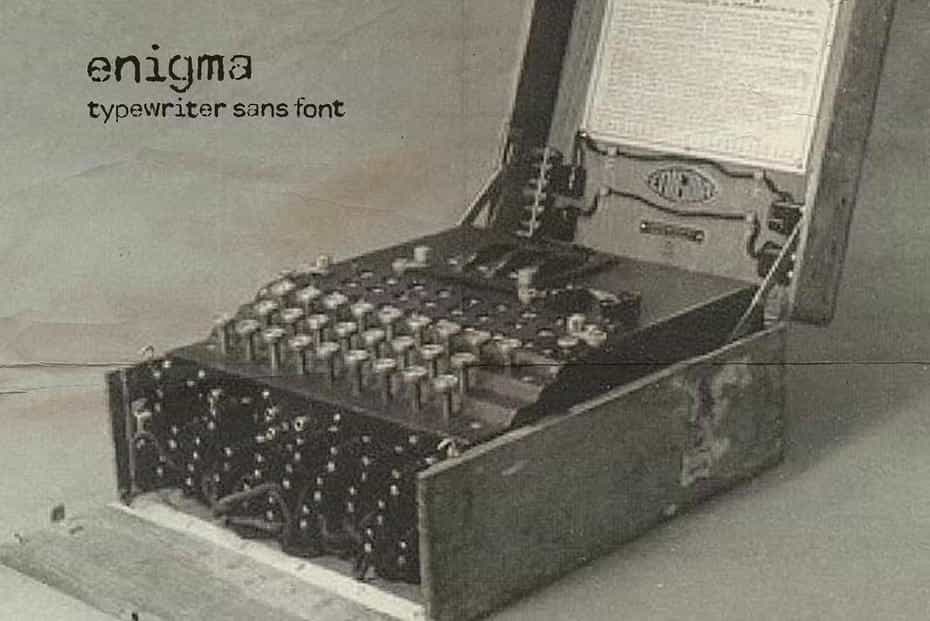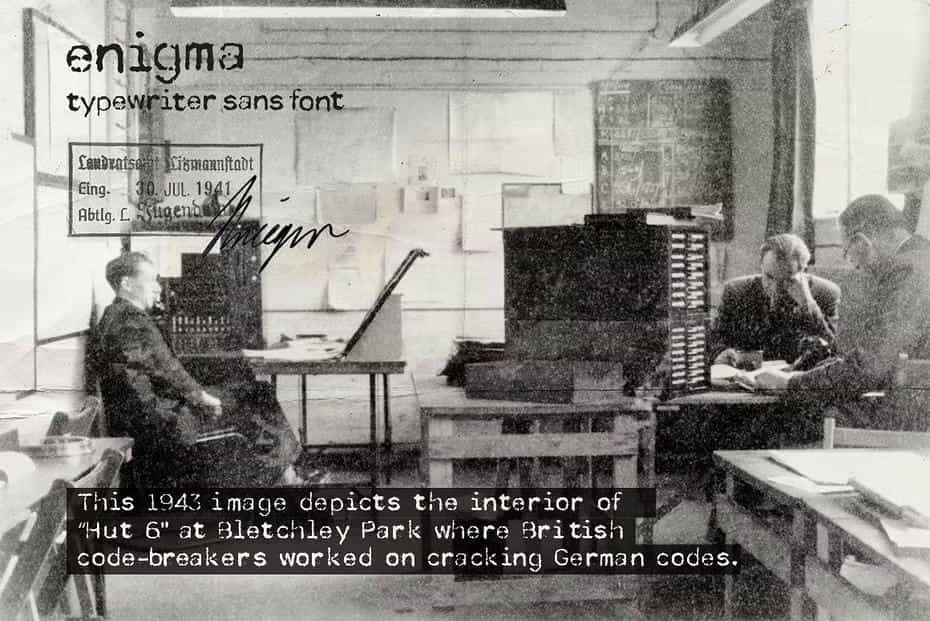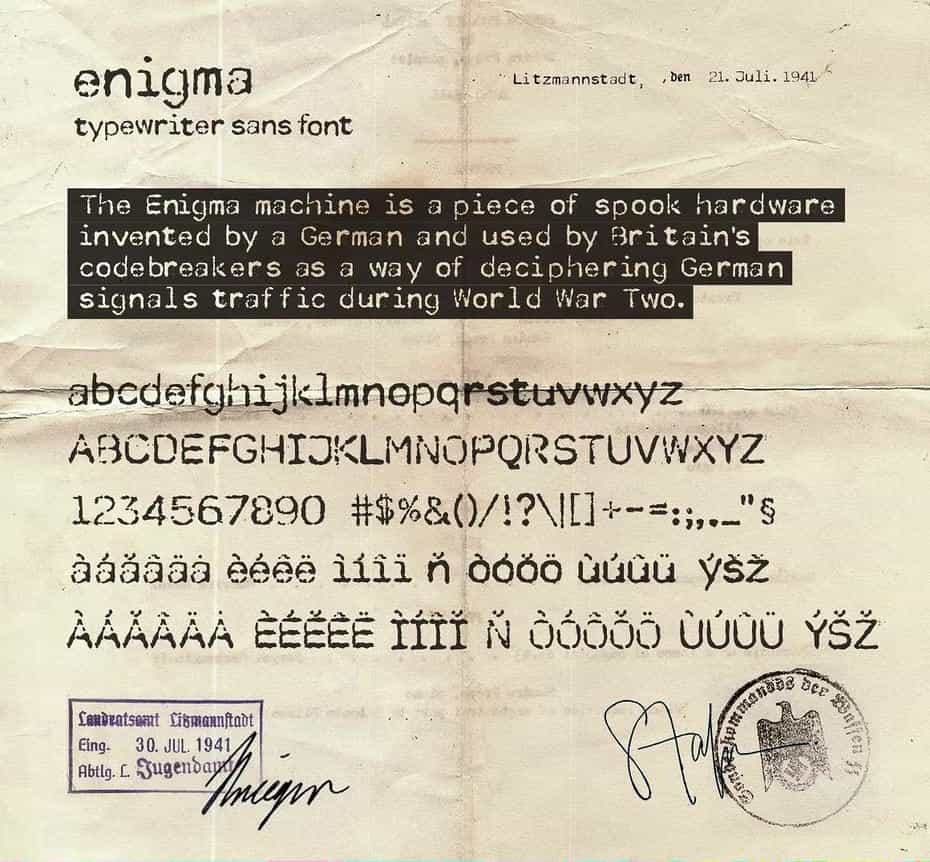
فونت انگلیسی Enigma Typewriter Sans Font : این مجموعه شامل فونت ماشین تحریر است که برای القای حس واقعی ماشین تحریر قدیمی طراحی شده است. شما می توانید در طراحی های مختلف از این فونت انگلیسی زیبا استفاده نمایید.
- سبک: Sans-Serif
- فضا بین حروف: Monospace